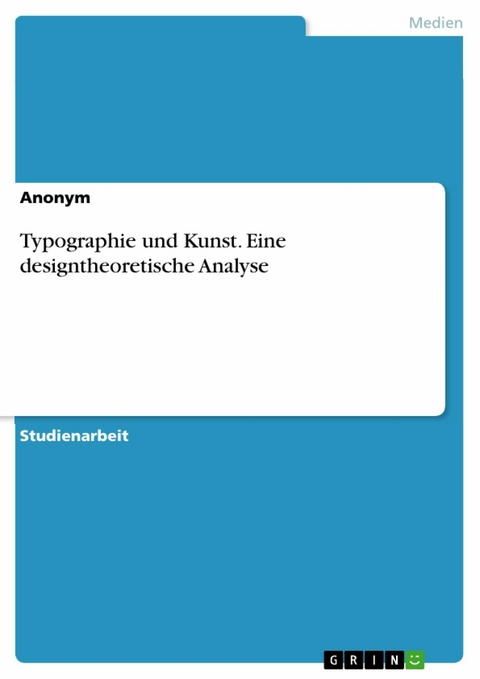
Typographie und Kunst. Eine designtheoretische Analyse (eBook)
Studienarbeit aus dem Jahr 2019 im Fachbereich Kunst - Grafik, Druck, Note: 1,0, , Veranstaltung: THINK BIG!, Sprache: Deutsch, Abstract: In dieser Hausarbeit wird das Thema Typographie durch eine designtheoretische Herangehensweise genauer untersucht und analysiert. Nachdem der Begriff der Typographie genauer definiert wurde, wird sich den Bereichen Kunst und Linguistik angenähert. Hierzu wird zunächst ein kurzer historischer Einblick in Geschichte der Typographie gegeben. Im weiteren Verlauf wird auf die Beziehung zwischen Form und Inhalt, der Wirkung und Macht von typographischer Gestaltung eingegangen. Auf dieser theoretischen Grundlage aufbauend, kann erneut ein Bezug zur Kunst hergestellt werden: Kunstvolle Typographie oder typographische Kunst? Hierzu wird die typographische Arbeit Palast des Zweifels des norwegischen Künstlers LARS Ø. RAMBERG untersucht und analysiert. Die theoretische Herangehensweise ist wichtig, um die Relevanz des Themas für den Schulkontext herauszuarbeiten. Somit wird im weiteren Verlauf der Arbeit der Frage nachgegangen, warum Typographie relevant für den Schulkontext ist. Hierzu werden die Fachlehrpläne der Fächer Kunst und Deutsch genauer untersucht und das fächerverbindende Unterrichtsprojekt Macht Typographie! für den Schulkontext vorgestellt. Die Hausarbeit hat somit einen schulisch relevanten Schwerpunkt.